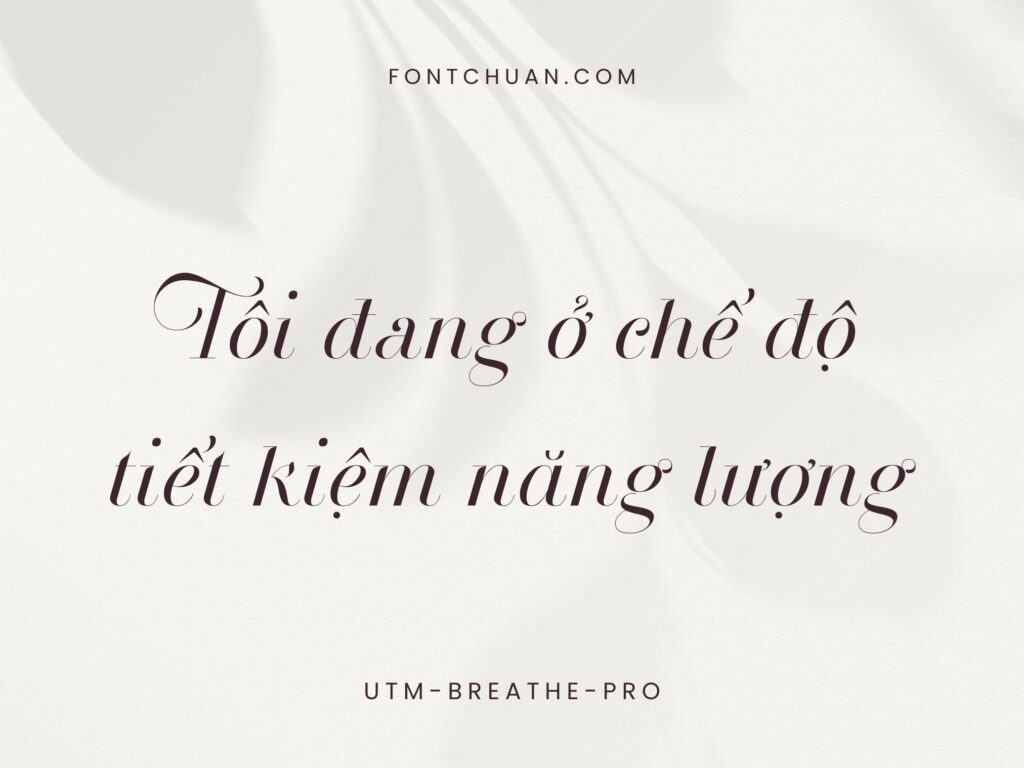
Font UTM Breathe Pro Việt Hóa
UTM Breathe Pro là phiên bản Việt hóa của font chữ Breathe Pro, một kiểu chữ thư pháp độc đáo, kết hợp giữa sự mềm mại, uyển chuyển và tính nghệ thuật cao. Font này nổi bật với các đường nét được vẽ tỉ mỉ, mang đến cảm giác nhẹ nhàng và tinh tế cho các dự án thiết kế. Phiên bản Việt hóa đã được thực hiện bởi Đinh Kiên, hỗ trợ đầy đủ tiếng Việt cùng hơn 100 ngôn ngữ khác. Đây là một trong những font được cộng đồng thiết kế sưu tầm và chọn lọc nhằm đáp ứng nhu cầu đa dạng trong thiết kế.
UTM Breathe Pro có cấu trúc chữ với các nét mềm mại và mượt mà, tạo nên sự nổi bật và thu hút. Font này phù hợp cho các ứng dụng như thiết kế logo, thương hiệu, bao bì sản phẩm và các ấn phẩm quảng cáo yêu cầu sự tinh tế và nghệ thuật. Các ngành nghề như quảng cáo, giáo dục, công nghệ và bất động sản có thể tận dụng UTM Breathe Pro để tạo điểm nhấn độc đáo trong thiết kế.